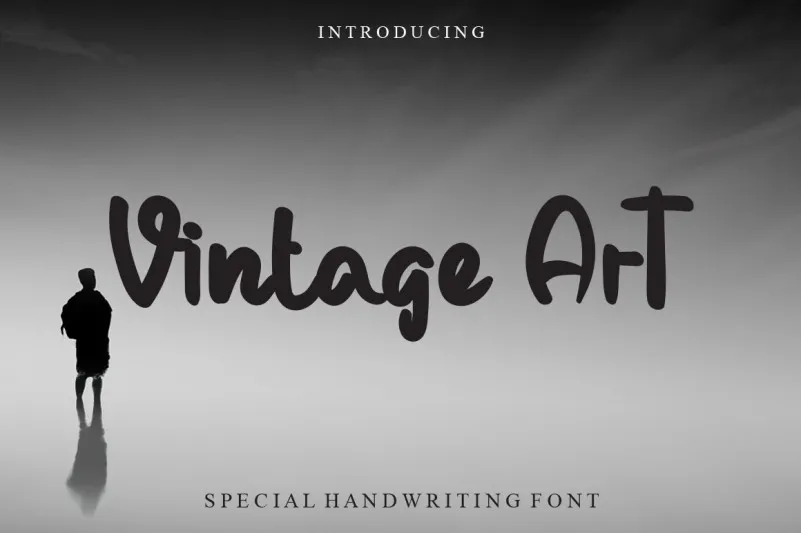
Vintage Art Font – Download Grátis
A Vintage Art Font é uma elegante fonte escrita à mão que combina rusticidade com modernidade. Com suas linhas curvas e clareza, ela se destaca para projetos criativos. Este tipo de letra é ideal tanto para uso profissional quanto para projetos pessoais, garantindo um touch de personalização única aos seus trabalhos. Perfeito para quem busca uma fonte que dê vida a qualquer texto ou design, esta fonte ficará entre os favoritos de designers e artistas graças ao seu charme único e à facilidade com que se integra a várias criações digitais. Seja em cartazes, ícones, logotipos ou até mesmo gráficos publicitários, Vintage Art Font vai torná-los irresistíveis e estilizados.